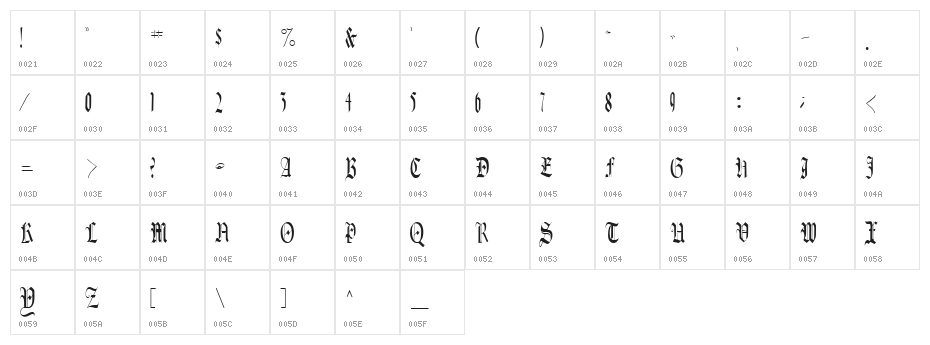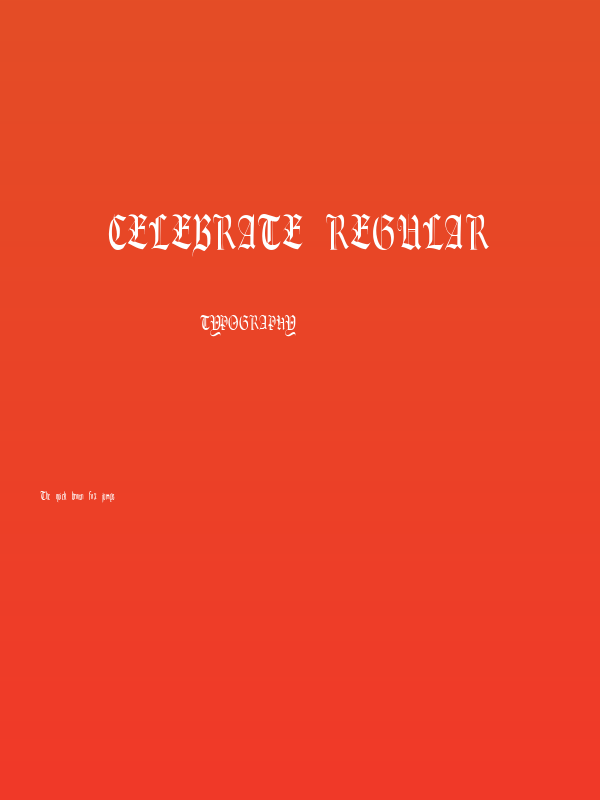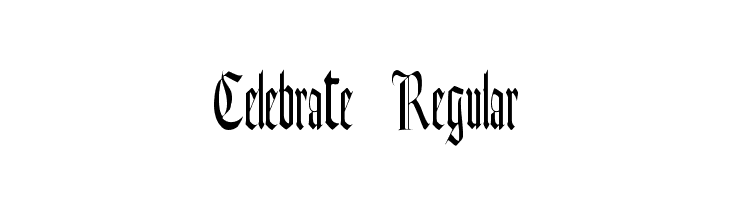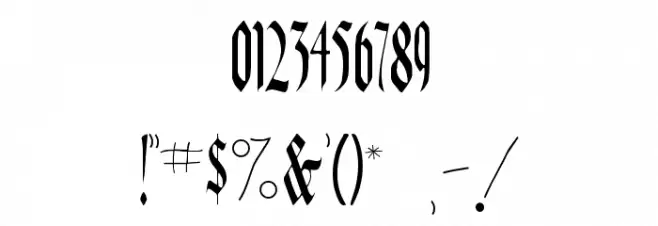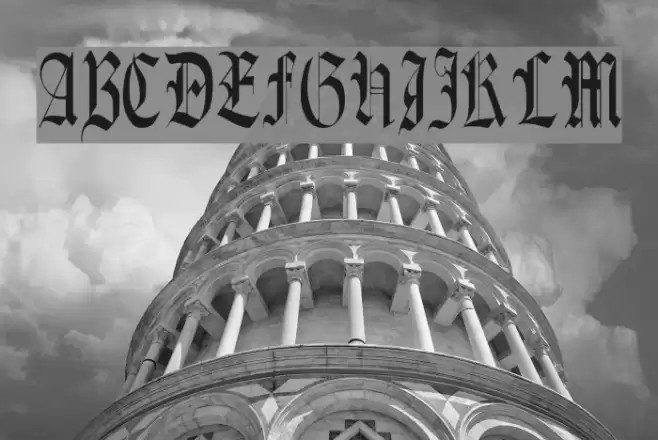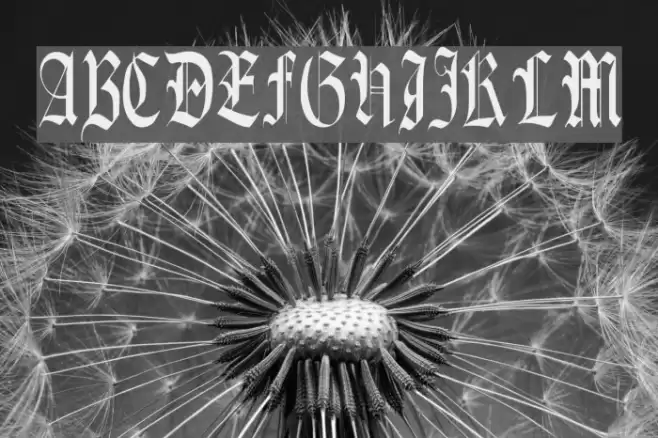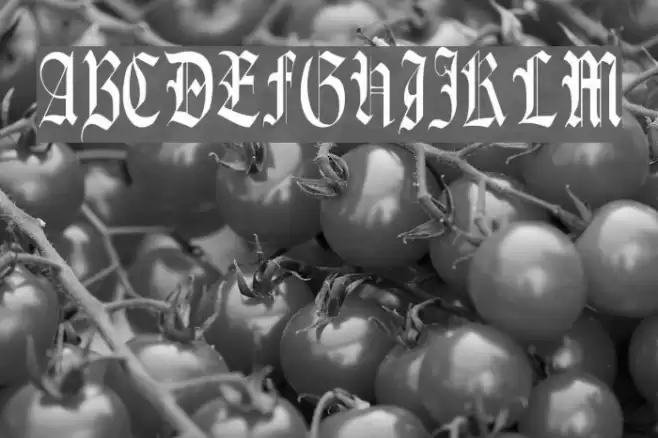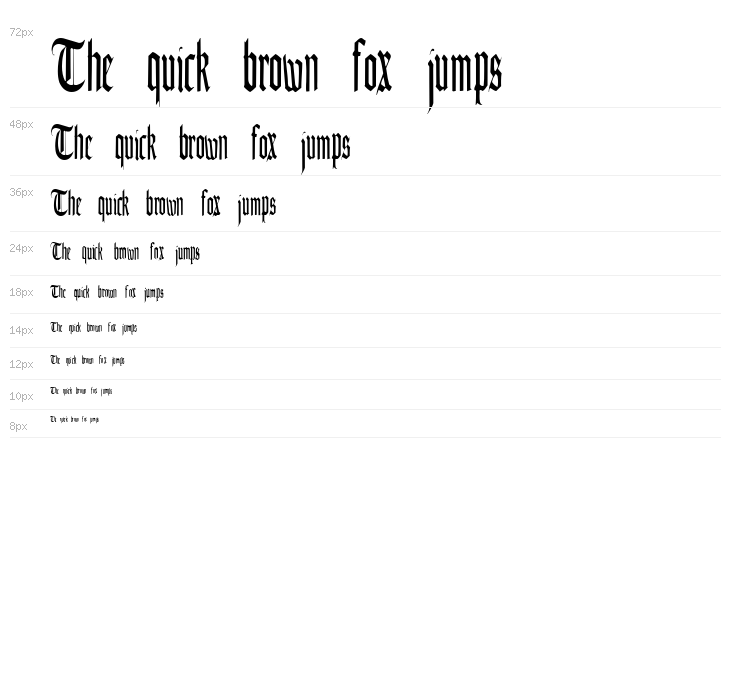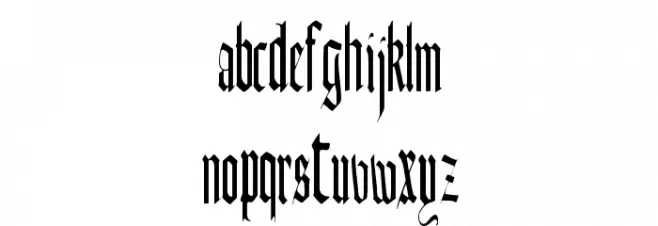
Celebrate Regular Font
✎ Gothic
| Категория | Gothic |
| Общий стиль | Vintage |
| Область применения | Headlines, Logos, Decorative text |
| Рекомендуемые проекты | Ideal for historical documents, medieval-themed designs, book covers, or any project requiring a dramatic, old-world aesthetic. |